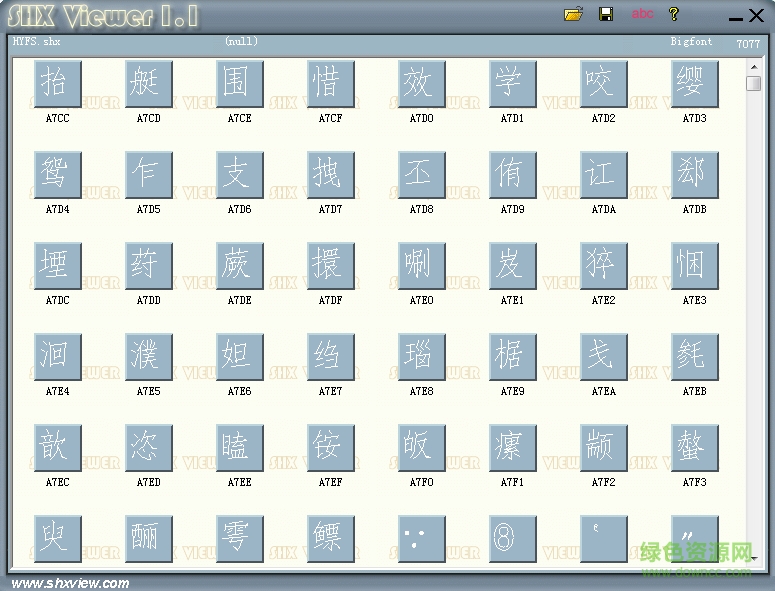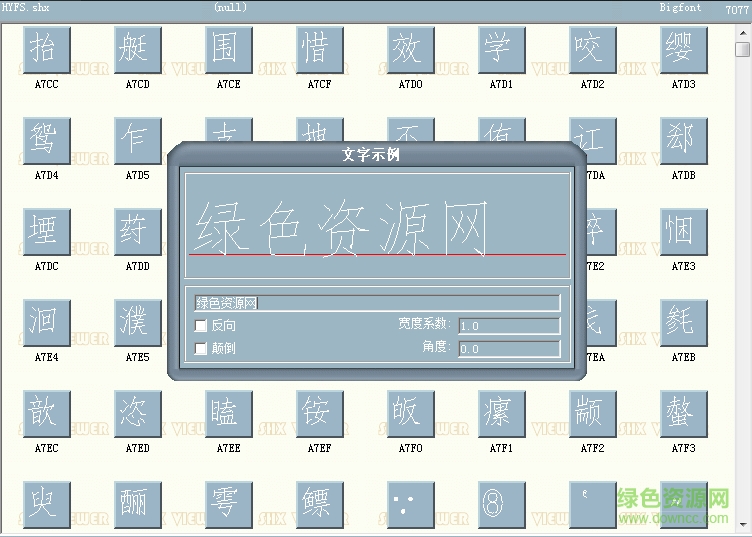
cad hyfs字體官網(wǎng)免費版是很多人找的一款的cad字體,該字體體積小,外形美觀好看,字體顯示效果出色,且支持中英文輸入,歡迎大家在綠色資源網(wǎng)下載!
關(guān)于 DWG 圖文件中使用的文字字體,可以分別選用 Windows「TrueType字體」或 autocad「SHX字體」這二種。
一、TrueType字體:使用者在 DWG 圖檔中比較常用的為「細明體」及「標楷體」
TrueType字體優(yōu)點可以同時顯示「英文/數(shù)字/中文」,缺點若是圖面中大量使用相當耗資源,會造成開圖及改圖延遲緩慢等狀況。當您使用特殊TrueType字體(如:華康中黑體、全真中圓體等其他字體),在其他的用戶計算機中若沒有這些特殊字體,系統(tǒng)將自動使默認字體替換。 注:選用「TrueType字體」時,無法選擇大字體。
二、SHX字體:使用者在 DWG 圖檔中比較常用的依照默認為「txt字體」及「chineset大字體」這二種。
txt(字體文件)主要用于顯示「英文/數(shù)字」,chineset(大字體文件)則用來顯示「繁體中文」,一般「文字型式」使用「SHX字體」及「SHX大字體」組合,優(yōu)點可以有效降低資源消耗,開圖及改圖不會有延遲緩慢等狀況。若是使用特殊SHX大字體(如:lsp.shx、china.shx等其他大字體),在其他的用戶計算機中若沒有這些特殊大字體,當開啟DWG圖文件時系統(tǒng)將會出現(xiàn)「替換字體」對話框,用戶需手動選擇替換大字體。
注:通常在亞洲使用SHX字體均需選用「大字體文件」,并依照不同版本語系選用不同的大字體文件(如:簡體中文字體gbcbig.shx 及 日文字體bigfont.shx 等其他字體)